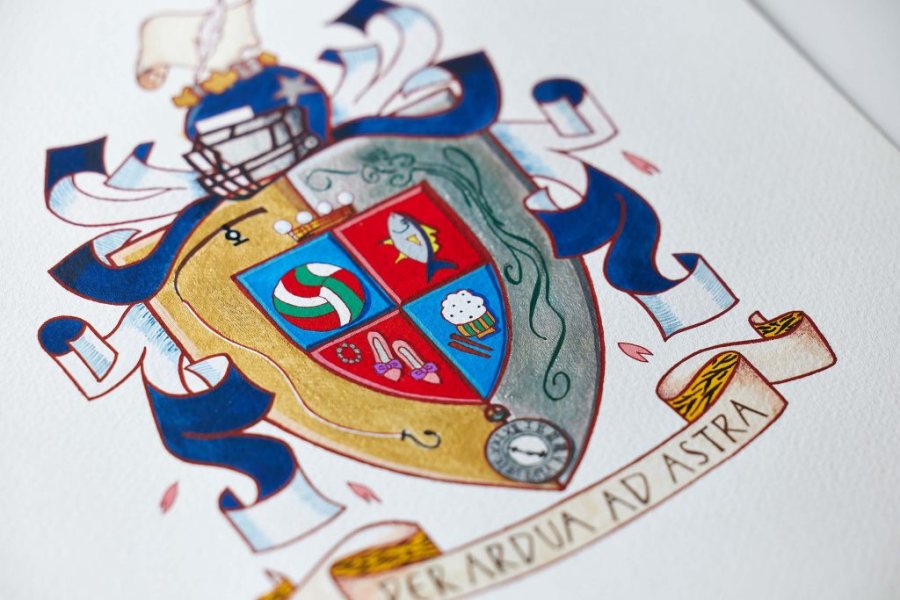
Die Kunst des Mentorings – Tradition trifft auf Moderne
Echoes of the Past – Kalligrafie trifft auf das Stundenbuch
Das Stundenbuch – ein kunstvoll gestaltetes Gebetsbuch aus dem Mittelalter – war einst ein fester Bestandteil des täglichen Lebens. Die darin enthaltenen Texte, illuminierten Buchstaben und filigranen Verzierungen zeigen nicht nur eine beeindruckende handwerkliche Meisterschaft, sondern auch tiefe Einblicke in die Gedankenwelt der Menschen vergangener Jahrhunderte. Doch was passiert, wenn Kalligrafinnen und Kalligrafen dieses historische Erbe neu entdecken und auf zeitgemäße Weise interpretieren? Genau das geschah in der Mentoring-Gruppe von Andrea Wunderlich, die sich unter dem Titel „Echoes of the Past: Inspired by The Book of Hours“ mit der künstlerischen Transformation dieser Tradition beschäftigte.
Das Mentoring-Programm von Andrea Wunderlich
Die renommierte Kalligrafin Andrea Wunderlich leitete von Februar bis November 2024 das Mentoring-Programm „The Art of Letters Mentoring Initiative“, in dessen Rahmen sie drei talentierte Künstlerinnen unterstützte:
Gemeinsam erforschten sie die Ausdruckskraft des mittelalterlichen Stundenbuchs und setzten dessen Elemente in einen modernen Kontext.
Das Programm richtete sich an Künstlerinnen, die sich über Jahre – insbesondere während der Pandemiezeit – durch Workshops auf ein fortgeschrittenes Level hochgearbeitet hatten. Obwohl sie handwerklich bereits sehr versiert waren, standen viele vor der Herausforderung, ihr Können professionell einzusetzen. Genau hier setzte Andrea Wunderlich als Mentorin an: Sie begleitete die Teilnehmenden in ihren künstlerischen Projekten und unterstützte sie mit Rat und Tat.
Über den Zeitraum des Mentorings hinweg erarbeiteten die Mentees individuelle Projekte, aus denen drei Arbeiten entstanden, die abschließend im November 2024 ausgestellt wurden. Darüber hinaus hielten sie zwei Vorträge: einen über sich selbst und ihr künstlerisches Projekt sowie einen weiteren zu einem freien Thema.
Künstlerische Vielfalt – Drei Perspektiven auf das Stundenbuch
Kalligrafie als Brücke zwischen Vergangenheit und Gegenwart
Jede der Mentees brachte ihre eigene künstlerische Handschrift und kulturellen Hintergrund mit ein. Das Ergebnis war eine faszinierende Sammlung von Arbeiten, die das Stundenbuch nicht als bloßes historisches Relikt begreift, sondern als Inspirationsquelle für eine neue Generation von Kalligrafen.
Hinter der Mentoring-Gruppe stand Dorothy Lim-Chew, eine leidenschaftliche Kalligrafin aus Singapur und Gründerin von „The Art of Letters“. Ihr Engagement für die Förderung der Kalligrafie-Szene zeigt sich in zahlreichen Initiativen, darunter der „Beginners’ Table“, der kostenlose Einführungen in die Kalligrafie bietet. Während der Pandemie kuratierte sie die Online-Ausstellung „Grateful“, in der Künstler:innen aus aller Welt ihre Dankbarkeit in kalligrafischen Werken ausdrückten.
Mit dem „Art of Letters Mentoring Programme“ schuf sie eine Plattform, auf der etablierte Künstler:innen ihr Wissen an Nachwuchstalente weitergeben. Andrea Wunderlich war eine von ihnen – und mit ihrer Gruppe von Mentees setzte sie ein eindrucksvolles Zeichen dafür, wie lebendig und dynamisch die Kalligrafie-Szene heute ist.
Das Stundenbuch neu gedacht: Eine Symbiose aus Geschichte und Gegenwart
„Echoes of the Past“ war mehr als ein künstlerisches Projekt. Es zeigte, dass Kalligrafie nicht nur eine Technik, sondern eine Brücke zwischen Epochen, Kulturen und Emotionen ist. Die Beschäftigung mit dem Stundenbuch machte deutlich, dass Schrift nicht nur ein Mittel zur Kommunikation, sondern auch ein Ausdruck der menschlichen Existenz ist.
In einer Zeit, in der digitale Medien immer mehr Raum einnehmen, erinnert dieses Projekt daran, dass Handschrift und Kalligrafie eine unvergleichliche emotionale Tiefe besitzen. Sie können Vergangenes bewahren, Geschichten erzählen und gleichzeitig neue Perspektiven eröffnen.
Fazit: Die Zukunft der Kalligrafie
Das Werk von Andrea Wunderlich und ihren Mentees war ein eindrucksvolles Beispiel dafür, wie Kalligrafie traditionelle Werte mit modernen Ideen verbindet. Die Auseinandersetzung mit dem Stundenbuch zeigte, dass alte Schriftkunst keine verstaubte Vergangenheit ist, sondern eine unerschöpfliche Inspirationsquelle für die Gegenwart und Zukunft.
Dorothy Lims Mentoring-Programm und das Engagement von Künstlerinnen wie Andrea Wunderlich trugen dazu bei, die Kalligrafie-Szene international zu vernetzen und neue Talente zu fördern. Wer sich für Schriftkunst begeistert, fand hier nicht nur ästhetischen Genuss, sondern auch eine tiefere Verbindung zur Geschichte – und vielleicht sogar zur eigenen Handschrift.